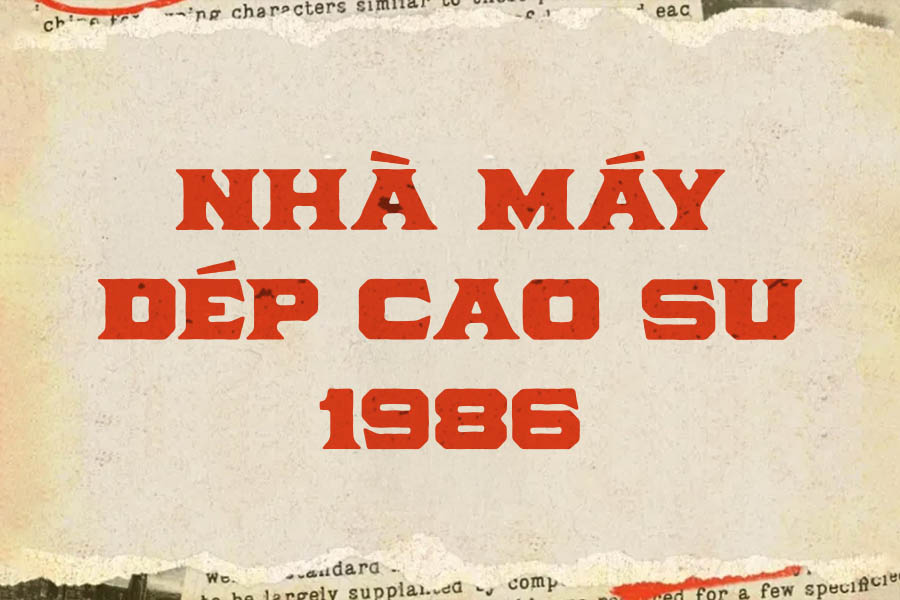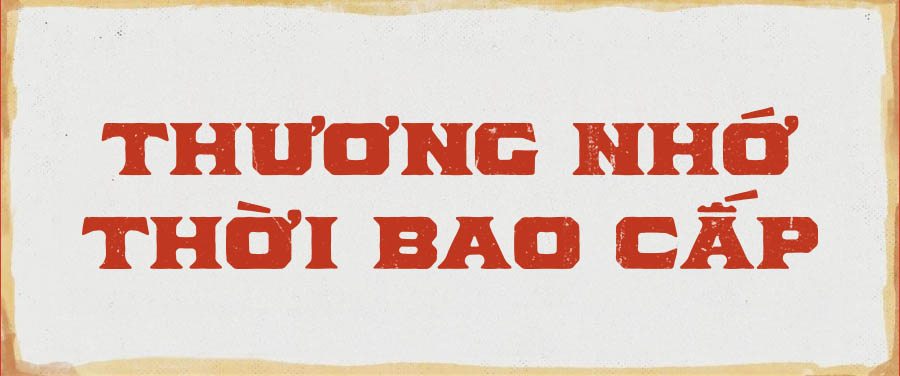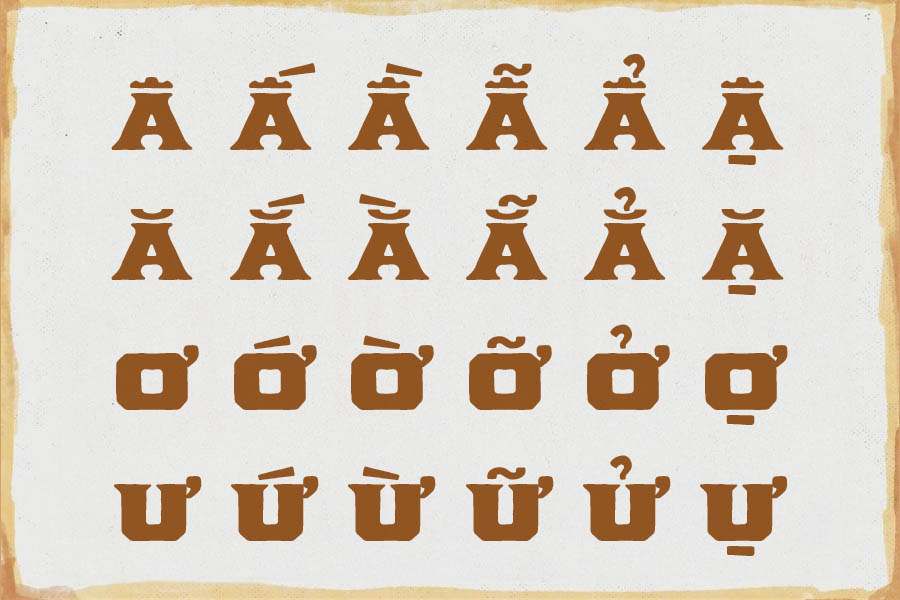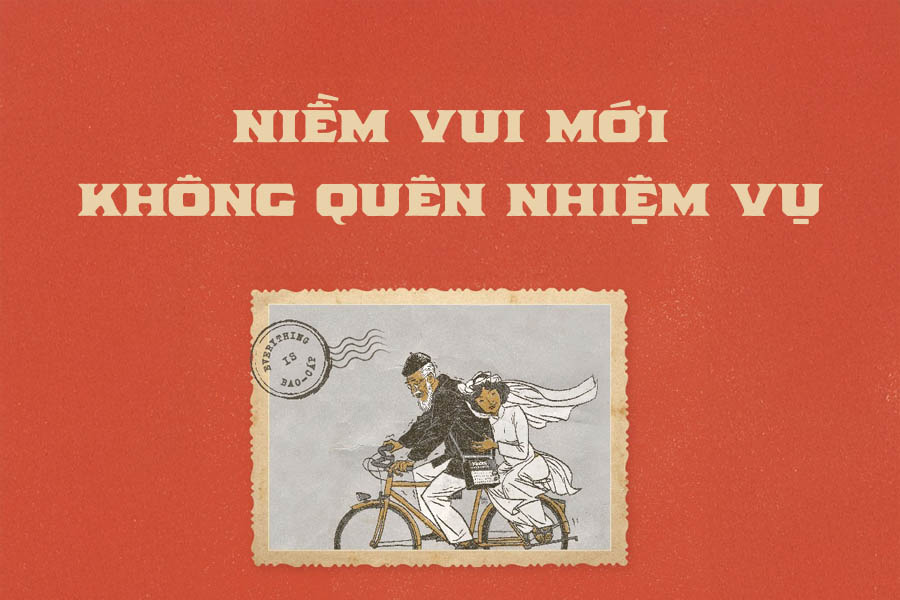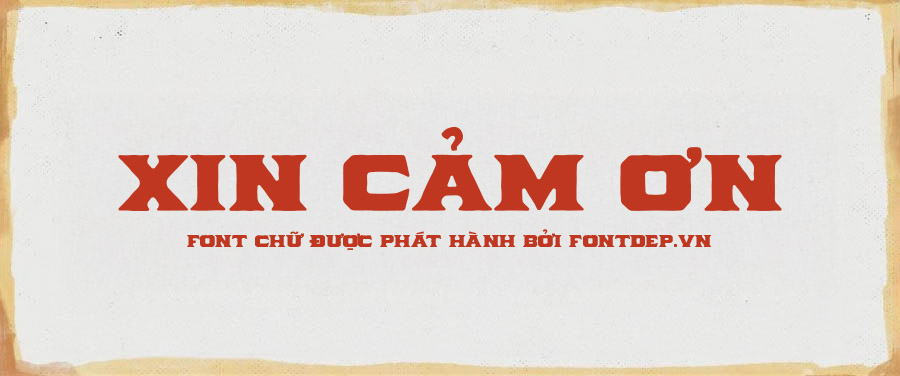
TH Hoaico 2 – Font Chữ Việt Hóa Mang Hơi Thở Thời Bao Cấp, Mộc Mạc và Hoài Niệm
Tác giả Grindstone
Trong ký ức tập thể của người Việt, giai đoạn bao cấp là một thời kỳ đặc biệt, mộc mạc, khó khăn nhưng đầy tình người. Những hình ảnh quen thuộc như bảng hiệu sơn tay, tem phiếu, bao bì gạo, xe đạp Phượng Hoàng... không chỉ mang giá trị lịch sử mà còn là chất liệu cảm hứng cho các nhà thiết kế hôm nay. Từ chính tinh thần đó, font chữ TH Hoaico 2 ra đời – một bộ font Việt hóa từ Grindstone (Ryan Martinson – Yellow Design Studio), tái hiện đậm nét phong cách hình ảnh thời kỳ bao cấp.
Kiểu dáng đậm chất công nghiệp cổ điển
TH Hoaico 2 mang phong cách slab serif với thân chữ dày, đường nét vuông vắn và chân chữ to bản. Các chi tiết được xử lý theo kiểu “in tay” hoặc “in lụa xưa”, tạo nên vẻ xù xì, thô ráp và có phần thủ công, rất giống với những dòng chữ được vẽ bằng sơn hoặc khắc gỗ trên biển hiệu cũ.
Điểm đặc biệt là các cạnh chữ không hoàn hảo: nét hơi gãy, đường bo không đều, có phần loang hoặc nứt nhẹ. Chính điều này khiến TH Hoaico 2 khác biệt với các font slab thông thường, mang đến cảm giác gần gũi, chân thực như những mảng ký ức còn nguyên bụi thời gian.
Phong cách mộc mạc đậm chất hoài cổ xưa
Khi nhìn vào dòng chữ dùng font TH Hoaico 2, người xem dễ liên tưởng đến các biểu ngữ, băng rôn tuyên truyền cũ, biển hiệu hợp tác xã, tem nhãn của các mặt hàng tiêu dùng thời bao cấp... Từ màu sắc thị giác đến độ thô nhám của các đường nét, font này đánh thức ký ức đô thị Việt trong giai đoạn lịch sử quan trọng của thế kỷ 20.
Font không chỉ dành cho những ai yêu sự hoài cổ, mà còn rất phù hợp với các dự án cần truyền tải tinh thần văn hóa bản địa, bản sắc vùng miền hoặc chất liệu thiết kế mang tính "chậm rãi – thật thà – xưa cũ".
Hệ thống dấu tiếng Việt được tối ưu
TH Hoaico 2 được Việt hóa đầy đủ, với hệ thống dấu thanh, dấu mũ, dấu trăng… được tinh chỉnh kỹ lưỡng để đảm bảo hiển thị đẹp, rõ ràng trên tất cả các nền tảng.
Điểm cộng lớn là dấu thanh được đặt gọn gàng trên các ký tự có chiều cao lớn như “A”, “O”, “U”, không gây cảm giác rối mắt hay lệch bố cục khi dàn hàng chữ in hoa. Đây là điều rất quan trọng khi sử dụng font slab trong tiếng Việt – một ngôn ngữ giàu thanh điệu và dấu phụ.
Ứng dụng thiết kế từ bảng hiệu đến phim tài liệu
TH Hoaico 2 không dành cho thiết kế bóng bẩy, hiện đại. Font này sinh ra để đồng hành cùng:
• Poster phim tài liệu, chủ đề lịch sử, chiến tranh, tái hiện xã hội xưa
• Bảng hiệu quán cà phê vintage, tiệm cơm, hàng quán mang phong cách bao cấp
• Ấn phẩm báo chí, sách ảnh tư liệu, triển lãm về Hà Nội – Sài Gòn thời xưa
• Bao bì đặc sản thủ công, nhãn mác sản phẩm truyền thống
Khi được kết hợp cùng chất liệu ảnh cũ, tone màu đất nung, vàng cháy, đỏ sậm… font chữ này lập tức kích hoạt chiều sâu cảm xúc và trí nhớ thị giác – điều mà không nhiều font hiện nay làm được.
Vì sao nên chọn TH Hoaico 2 thay vì các font retro phương Tây?
Rất nhiều font mang phong cách retro hiện nay được thiết kế cho thị trường Âu – Mỹ, vì thế khi sử dụng trong ngữ cảnh Việt Nam sẽ bị “lạc tone”, không khớp về mặt văn hóa thị giác.
TH Hoaico 2 tuy được chuyển thể từ font gốc Grindstone của phương Tây, nhưng nhờ quá trình Việt hóa kỹ lưỡng và tinh chỉnh lại tỷ lệ, khoảng cách, dấu thanh… nên hoàn toàn thích hợp cho người Việt sử dụng. Nó không chỉ là font chữ – mà còn là một phần của ký ức được gợi lại qua con chữ.
Trong thời đại mà thiết kế ngày càng chú trọng đến bản sắc, thì TH Hoaico 2 là một lựa chọn lý tưởng cho những ai muốn kể một câu chuyện bằng con chữ – mộc mạc, hoài niệm, chân thật và mang “chất Việt” rõ ràng.
Nếu bạn đang tìm một font vừa đủ mạnh để tạo điểm nhấn, vừa đủ “bụi” để tạo chiều sâu cảm xúc, hãy thử TH Hoaico 2. Có thể bạn sẽ thấy mình như được chạm tay vào một lát cắt lịch sử – ngay trên mặt chữ.